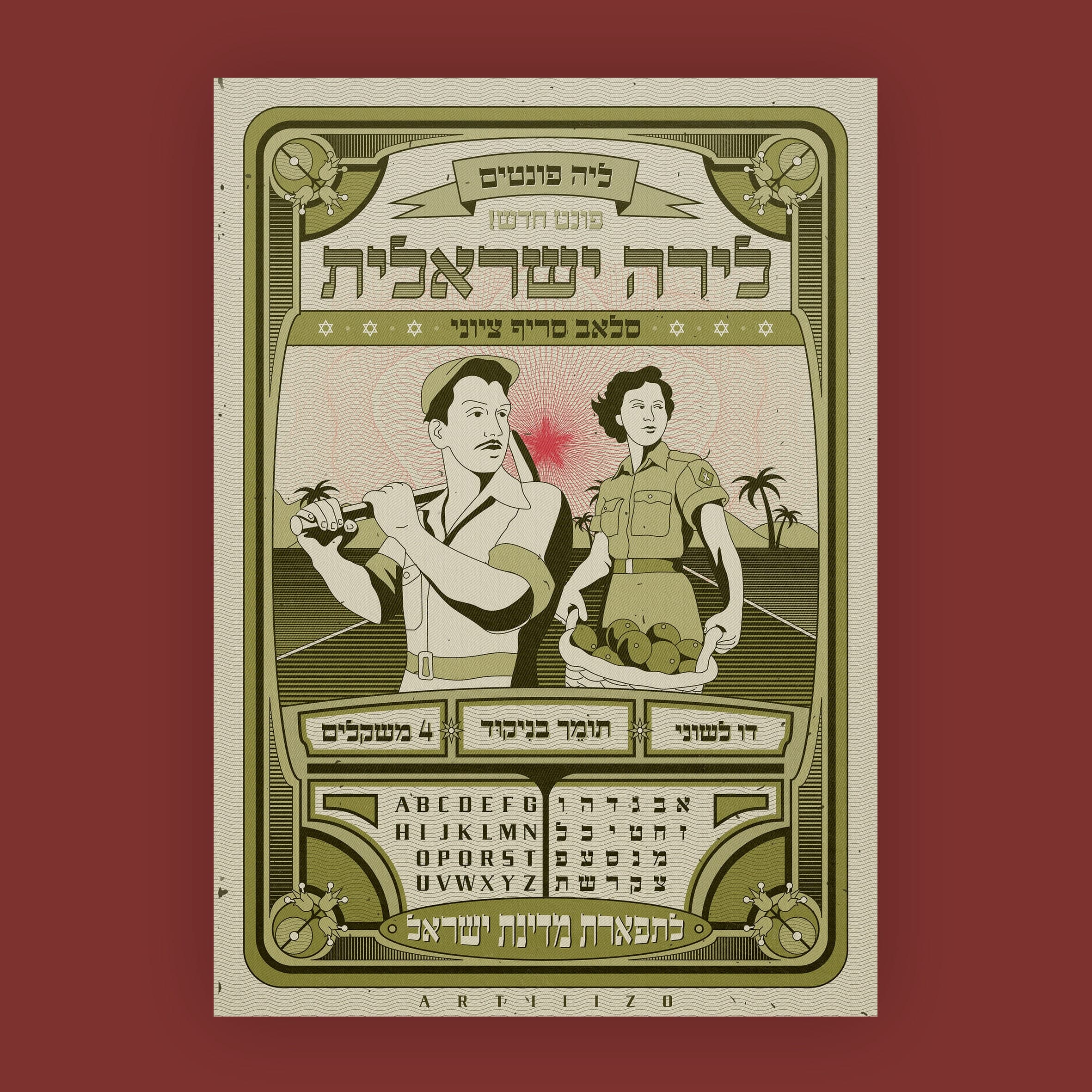
כשהכרזנו אי שם בכ״ט בנובמבר 1948 על הקמת מדינת ישראל, ירשנו, יחד עם כל הטוב והפחות שהותירו לנו הבריטים, גם את מערכת המטבע המנדטורית שכללה את הלירה הארץ-ישראלית. הלירה הזו נחלקה ל-1,000 מיל, והייתה שוות ערך ללירה שטרלינג הבריטית. לקראת סיום תקופת המנדט, בפברואר של אותה השנה, הוציאה הממשלה הבריטית את הלירה הארץ ישראלית מגוש השטרלינג.
בין ההחלטות שהתקבלו במסגרת הקמת המדינה, הוחלפה מועצת המטבע של המנדט בבנק אנגלו פלשתינה של הסוכנות היהודית ונקבע כי הוא זה שינפיק את שטרות המדינה.
התהליך הזה לא עבר חלק כל כך, והתגלעו בו מספר קשיים.
ראשית, עד כמה שזה יישמע לכם מצחיק, עדיין לא הוחלט על שם המדינה. גם מהבחינה הטכנית היה מורכב, משום שכדי להדפיס שטרות באיכות גבוהה נזקקנו עדיין למדפיס זר, וכדי להדפיס את השטרות על ידי American Bank Note Company, נדרש אישורה של מחלקת המדינה. כדי להימנע מסיבוכים הוחלט אם כן שלא לכתוב את שם המדינה, ורק לאחר הדפסת השטרות הוטבעו עליהן בנפרד המילים: "מטבע חוקית לתשלום כל סכום שהוא״.
עיצוב השטרות היה גנרי בעליל והתבסס על המקובלות הסטנדרטית באותם ימים, אבל מה שתפס את עיניי היה הפונט הנוכח שלהם. השטרות החדשים הגיעו לארץ ביולי 1948, ובאוגוסט עבר החוק שהכריז עליהם כעל חוקיים, בכך נכנסו לשימוש שוטף. תהליך החלפת שטרי הכסף המנדטוריים של מועצת המטבע הבריטית בשטרות החדשים של בנק אנגלו פלשתינה הושלם בחודש אוקטובר.
בשנת 1951 ירש בנק לאומי לישראל את כל נכסיו והתחייבויותיו של בנק אנגלו-פלשתינה, ושם כבר הונפקה סדרה שטרות חדשה, שעיצובה גם הוא דמה לשטרות הקודמים, רק שאז המטבע היה לירה ישראלית והמנפיק שלה היה חברה ישראלית לכל דבר.
על הפונט, אגב, לא ויתרו, והוא נשאר אותו דבר. קלאסי מחד ונעים מאד לעין, אך עוצמתי ומלא אמירה מאידך. בחירתו לשטרות בנק מעולם לא הפתיעה אותי, כי התאמתו מובנת. הוא משדר יציבות ואמינות, והמון רשמיות. אם תרצו, פונט שאפשר לסמוך עליו. ברמה העיצובית הוא נקי מאד, מה שמחדד את התאמתו למסמכים פורמליים וכאלה שצריכים לשדר אמינות, כמו שטרות כספיים למשל:)
עם השנים הוחלפו השטרות מספר פעמים נוספות, והרבה כסף זרם בנהר הבנקים הישראלי. הפונט הפך לנחלת העבר.
אבל כעת, בחרתי להחיות אותו.
הפונט החדש נשען בעיצובו על הפונט הרשמי והמהוקצע של שטרות הלירה הישראלית, עם שינויים והתאמות בני זמננו. הוא משדר את אותה יציבות ואמינות, ויתאים גם הוא למסמכים פורמליים או עבודות בהן תחפשו להותיר רושם מקצועי ונקי במיוחד, אבל הוא מודרני יותר וקיבל תוספת מסוימת של הקלילות של 2024. הגופן החדש יתאים למסמך שתרצו שמי שיקרא אותו יסמוך עליכם. הוא מופיע ב-3 משקלים והינו דו לשוני.
השילוב של הפונט הישן עם הכלים שיש כיום בידינו ליצירת פונטים הצליח מצד אחד לשמור על תכונות המקור אבל גם להתאים את עצמו לצרכים טכנולוגיים ואסתטיים עכשוויים.
נחמד לחשוב שנוכל שוב לעשות שימוש באותו כתב שהופיע בשטרות של בנק ציוני שפעל עוד לפני קום המדינה 🙂